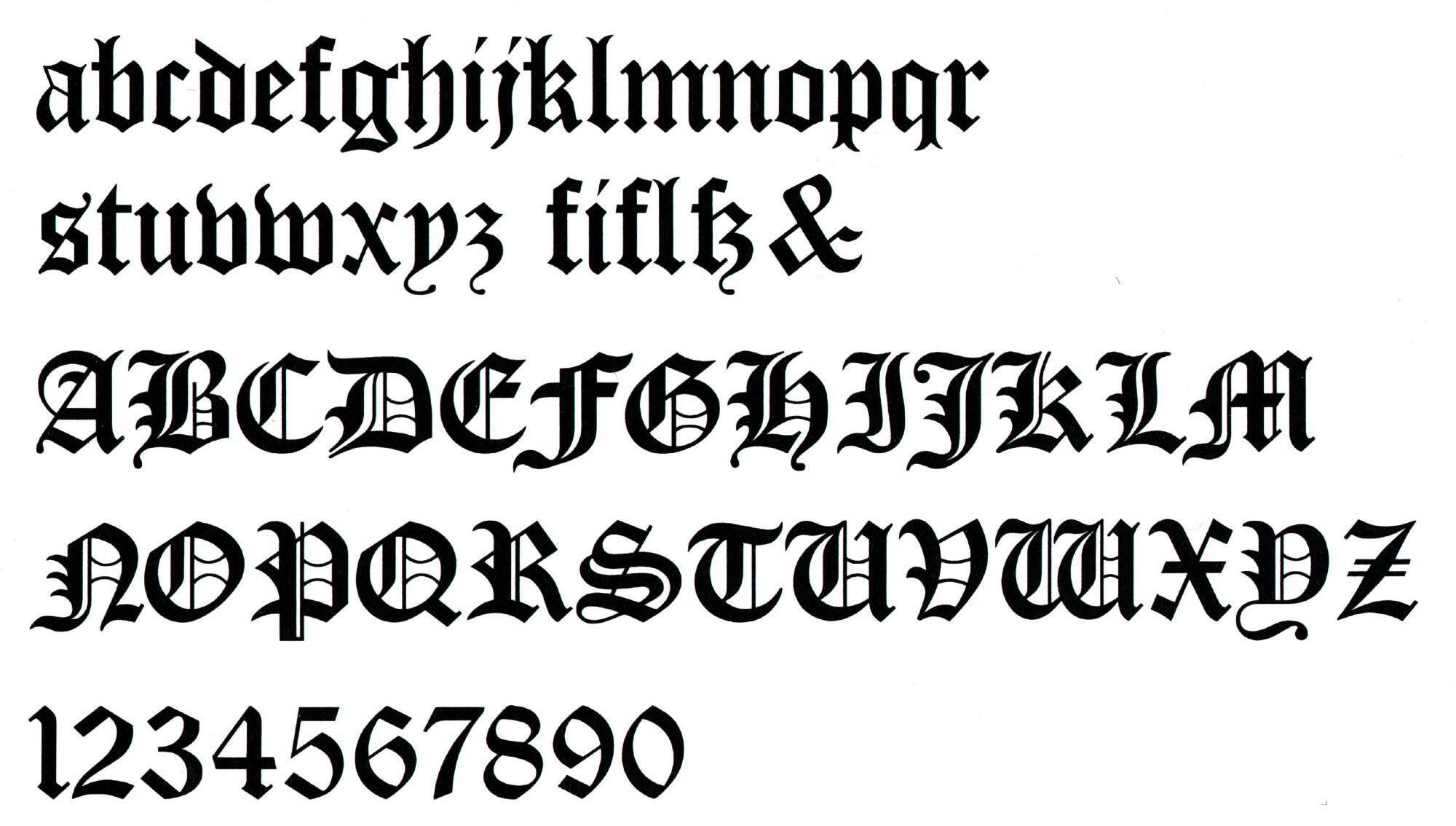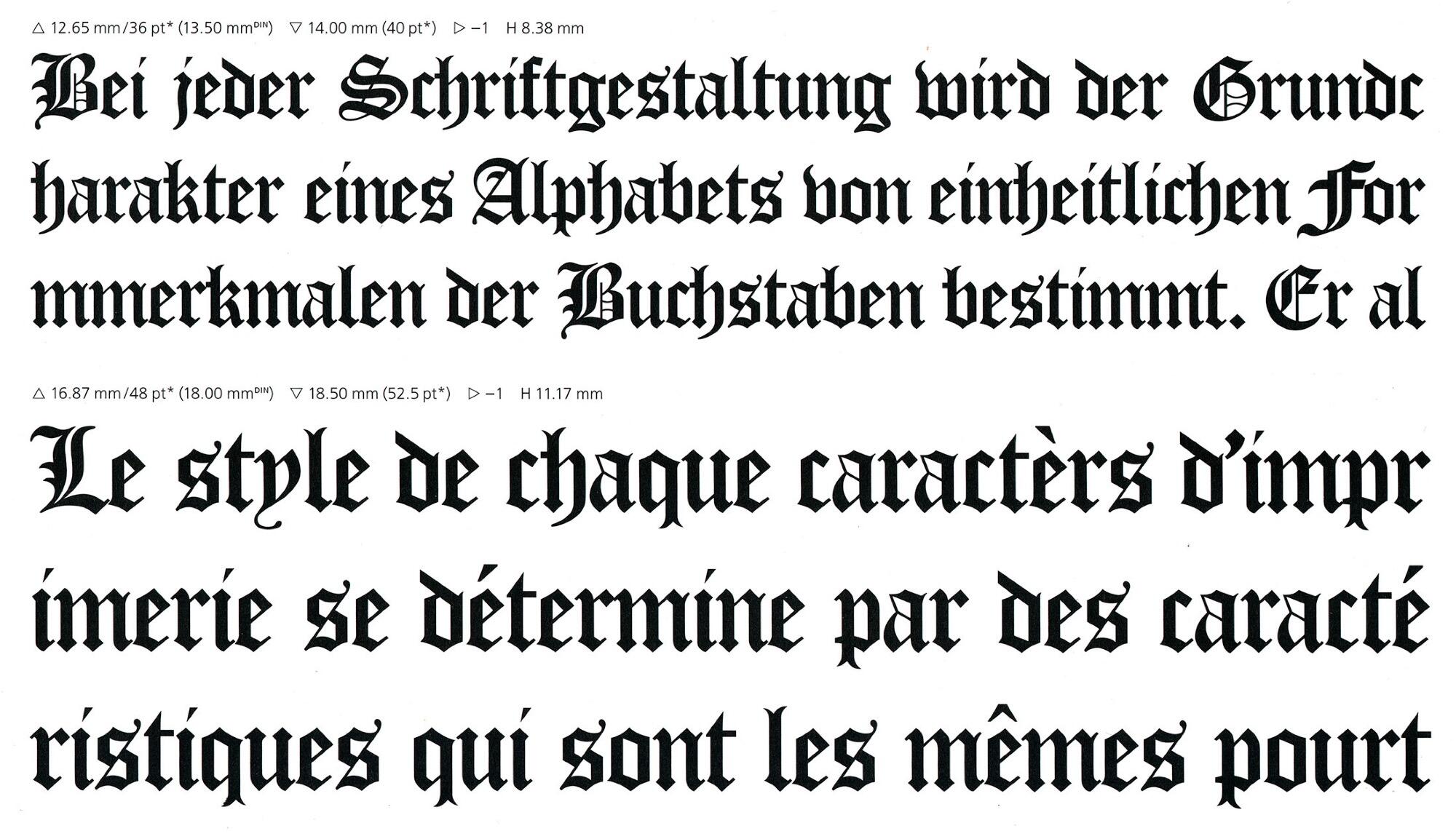
- 1904
- Gebrochene Schrift
Die Cloister Black ist eine gotische Schrift, die 1904 bei American Type Founders erschien. Digitale Versionen in einem Schnitt gibt es von Castle Type, Bitstream und Tilde.